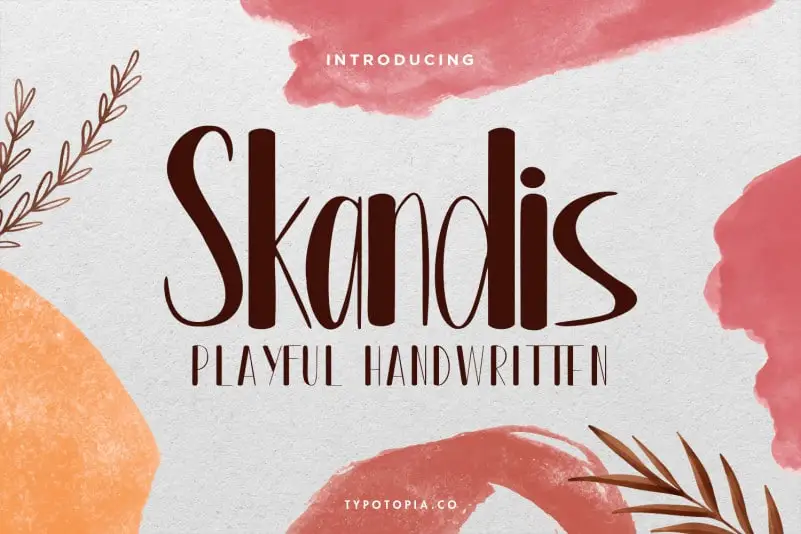
A Skandis Playful Display Font é uma escolha perfeita para quem busca algo diferenciado no seu design. Especialmente projetada para entusiasmar e surpreender, essa fonte script capta a atenção de forma única e sofisticada. Seja você um criador em desenvolvimento de logomarcas, um estilista que quer personalizar uma peça de arte impressa ou até mesmo alguém que busca uma maneira diferente para dar vida à embalagem de seu produto, a Skandis Playful Display Font pode ser o ponto final perfeito. Com ela, você cria elementos como cartões de visita, cartazes e rótulos com um toque vibrante e moderno. E não se esqueça dos desafios da moda – desde aparelhos até estampas de camisa. Em resumo, a Skandis Playful Display Font é uma ferramenta indispensável para quem busca inovação em seus projetos de design.